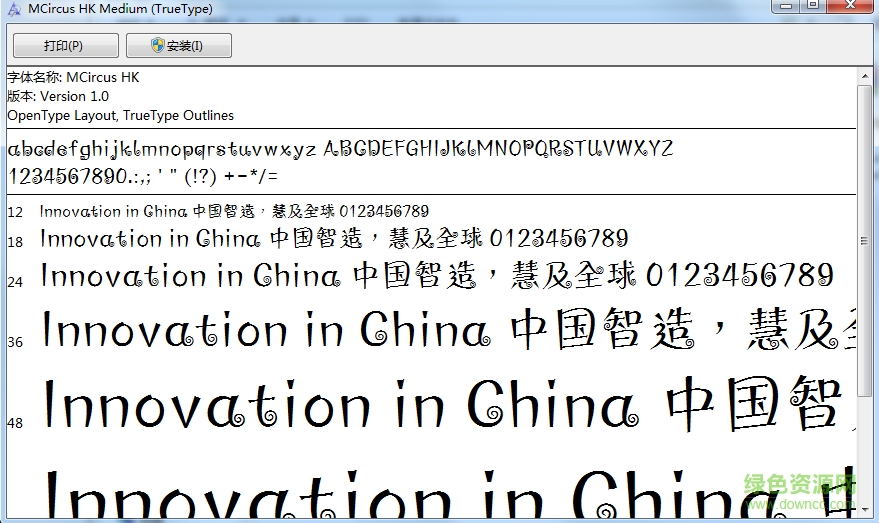
蒙納雅蔓簡(jiǎn)體
蒙納雅蔓簡(jiǎn)體是一款中文簡(jiǎn)體輸入的蒙納字體,字體尾部微卷,充滿活潑可愛(ài)之風(fēng),適用于海報(bào)設(shè)計(jì)、文字印刷等諸多行業(yè),而且還能適應(yīng)多個(gè)場(chǎng)景使用,無(wú)論是哪個(gè)行業(yè)都是可以直接用哦,歡迎大家下載!